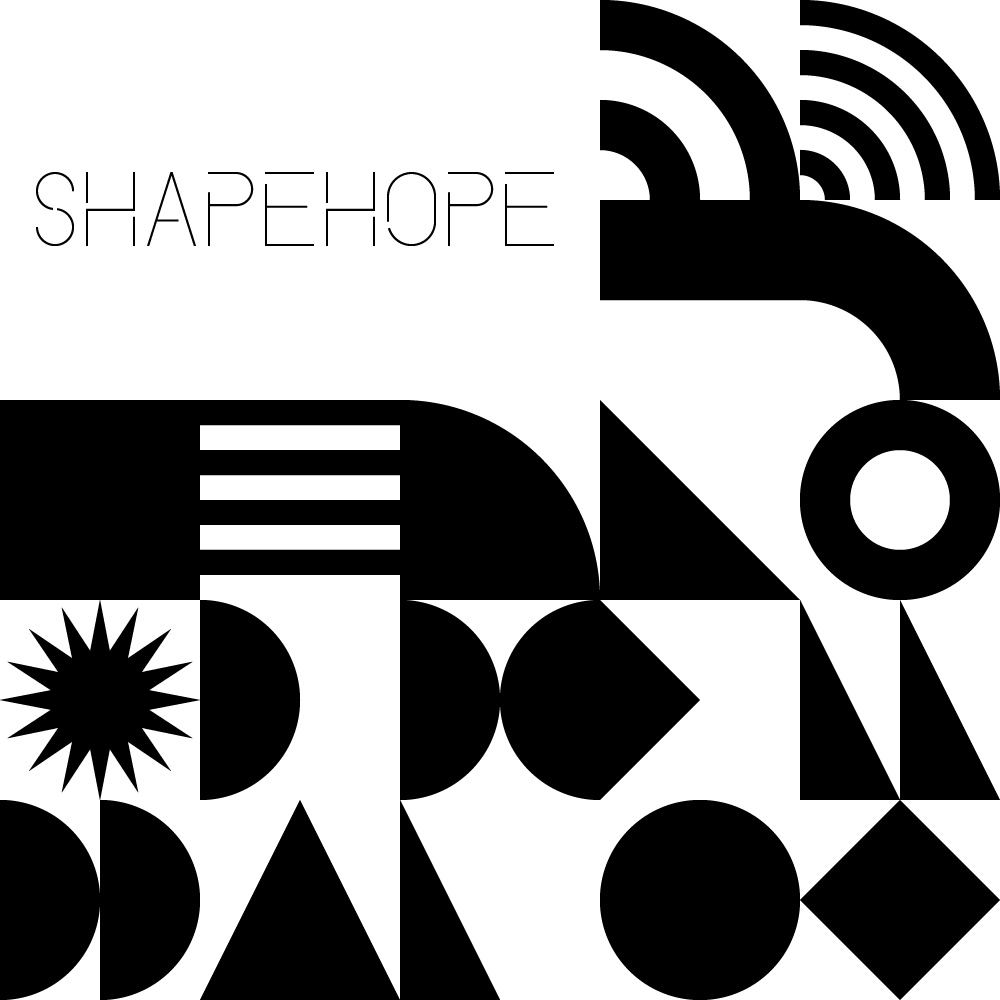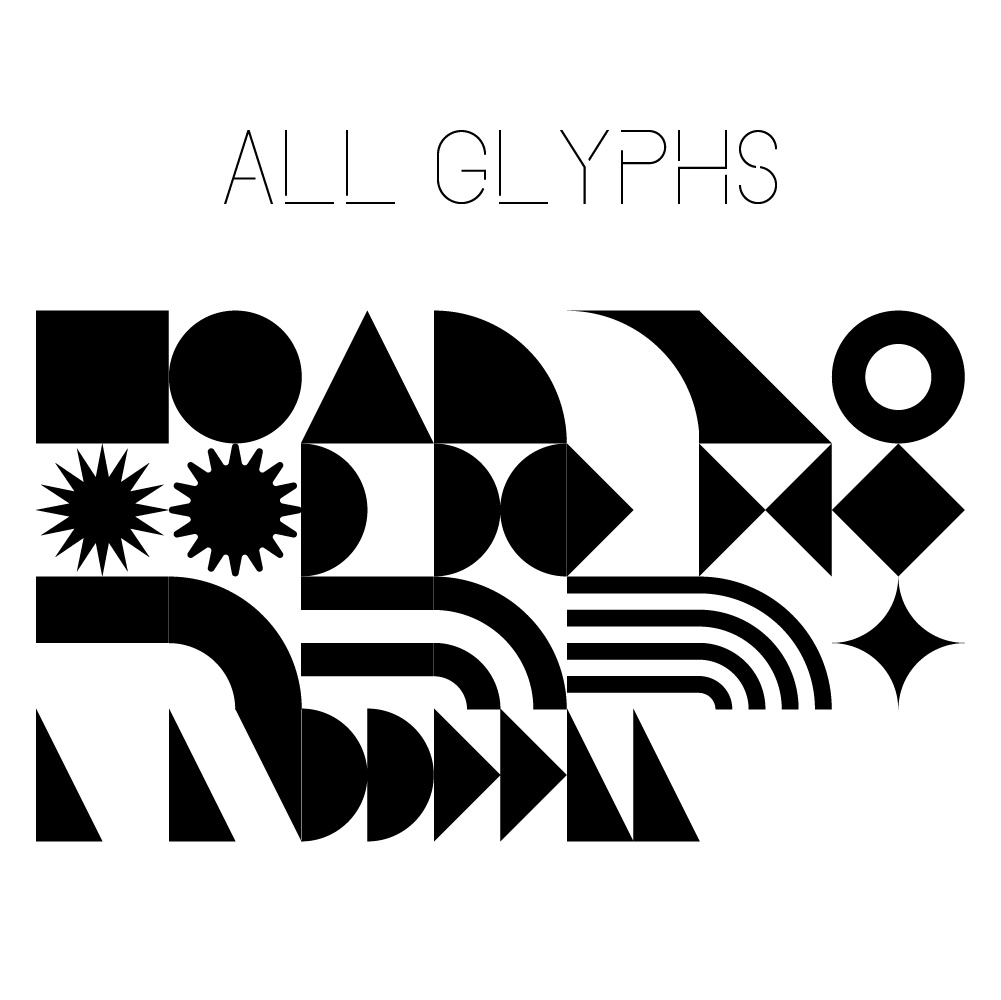
オリジナル図形フォント「ShapeHope」
ShapeHopeは正方形の中に収まる色々な形のシェイプを集めたフォントです ShapeHopeを使ってタイリングした背景を置くだけで良い感じの背景を作ることができます
・大文字 A-Z(26字)(この文字にシェイプが入っています) ・半角スペース ※小文字キー(a-z)を打っても、同じ大文字の字形が出ます。 ※数字・約物(記号)・かな・漢字は収録していません。これらを入力した場合、文字は表示されません。